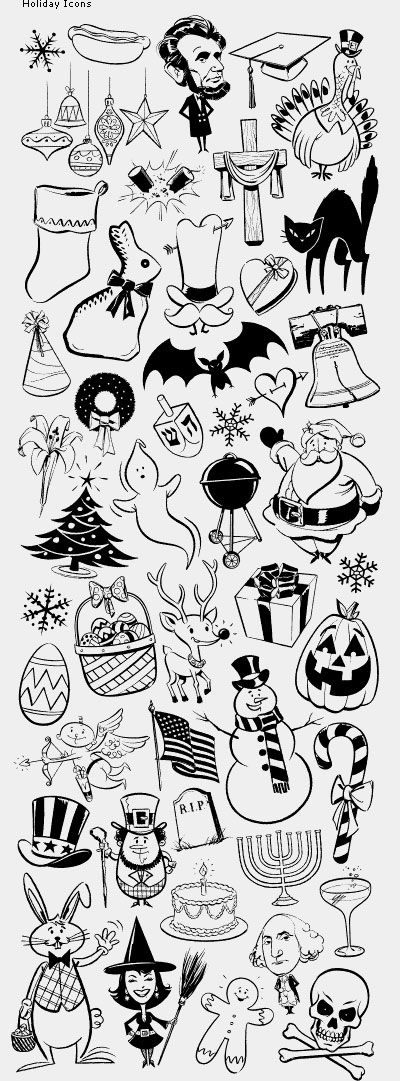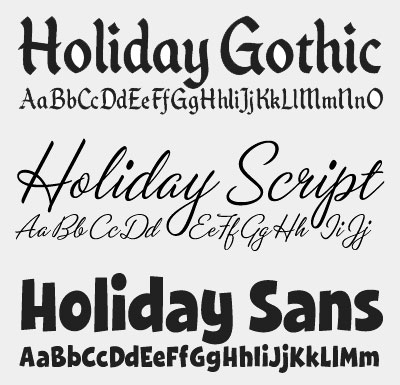
House Industries starten Holiday-OffensiveMit einem bunten Sortiment von Jahresendprodukten erfreuen House Industries
die Gemeinde der Schriftenfreunde. Neben drei neuen Fonts für die
Feiertagsgrüße (einschließlich typischer House-Illustrationen),
bietet die US-Designtruppe erstmals Grußkarten (zwei Formate,
![]() Zu den drei festlichen Schriften im Blackletter-, Script- und
Funny-Gothic-Stil schreiben die Herausgeber: »With some holiday
always around the corner, uber families, amateur display typefaces and overused
system fonts are not going to help you make that looming design deadline. These
three timeless gems plus the 48 festive icons will always be in season, so you
won’t have to worry about picking through that endless type menu
anymore.«